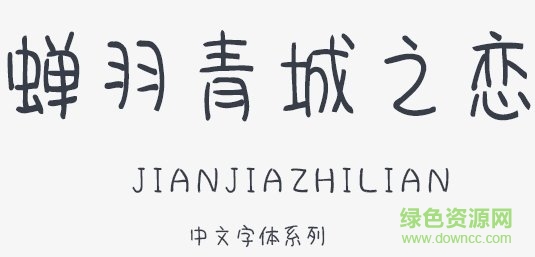
蟬羽青城之戀字體是蟬羽字體的最新手寫字體,整體風(fēng)格輕柔舒緩,給人簡潔舒適的視覺美感,喜歡的朋友不妨來綠色資源網(wǎng)你下載收藏!
蟬羽青城之戀簡體是一款個性手寫字體,字形活潑可愛、布白均勻,適用于媒體顯示和廣告設(shè)計(jì)等領(lǐng)域應(yīng)用。
蟬羽青城之戀簡體系列字體都極為娟秀精簡,圓潤的筆畫讓文字更顯藝術(shù)感,可以廣泛使用在平面設(shè)計(jì)、藝術(shù)設(shè)計(jì)、海報設(shè)計(jì)等諸多場合當(dāng)中,給你的創(chuàng)意作品帶來獨(dú)特體驗(yàn)!